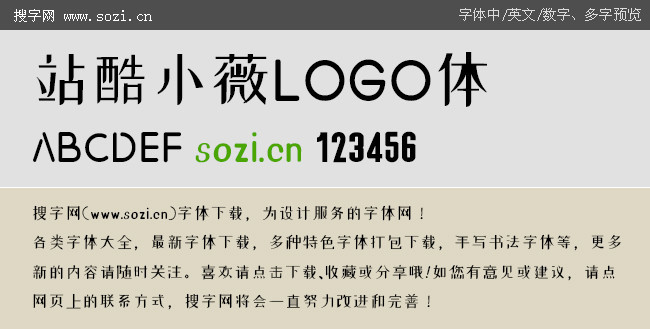
站酷小薇LOGO體
搜字網(wǎng)提供一款站酷小薇LOGO體中文字體下載,站酷小薇LOGO體是設(shè)計(jì)師李大衛(wèi)送給女兒三周歲的禮物,由上海佐茲品牌設(shè)計(jì)工作室設(shè)計(jì)總監(jiān)李大衛(wèi)帶領(lǐng)其工作室團(tuán)隊(duì)共成完成。設(shè)計(jì)師除了想把這款字體作為送給女兒的禮物,一個(gè)更大的愿望是希望這款字體可以填補(bǔ)免費(fèi)字體中LOGO體的空缺。站酷小薇LOGO體設(shè)計(jì)大膽創(chuàng)新,筆畫與劍身相似,修長、謙和、靈秀,在簡略了一些原字筆畫的同時(shí)依然保持了很高的識(shí)別性高,是標(biāo)志,標(biāo)題的神器。采用GB2312漢字編碼,共收錄6763個(gè)漢字。免費(fèi)授權(quán)全社會(huì)使用(包括商用)。